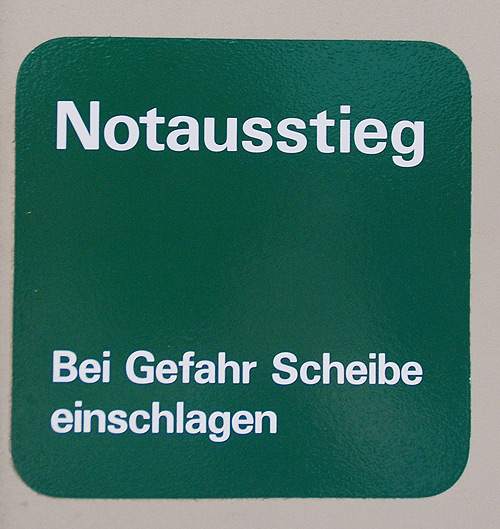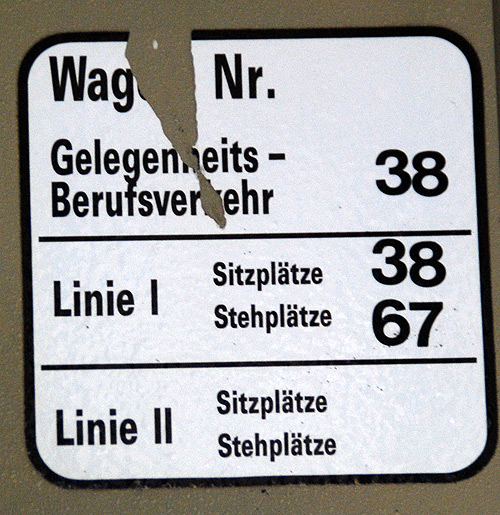
Welche Schrift ist auf dem Notausstieg-Schild (siehe Bild)?
Univers bold
Und das hier? Ich dachte erst, es ist dann eine Condensed-Variante.
Aber die Univers Condensed Bold sieht ganz anders aus. :-(
Ist das eine völlig andere Schrift (es geht um die Texte, nicht um die Ziffern rechts)??
Wie oben, nur horizontal gequetscht.
Das dachte ich auch erst … müssten dann aber die horizontalen Linien nicht deutlich dicker sein? Irgenwie sieht mir die schmale sehr ausgeglichen aus …